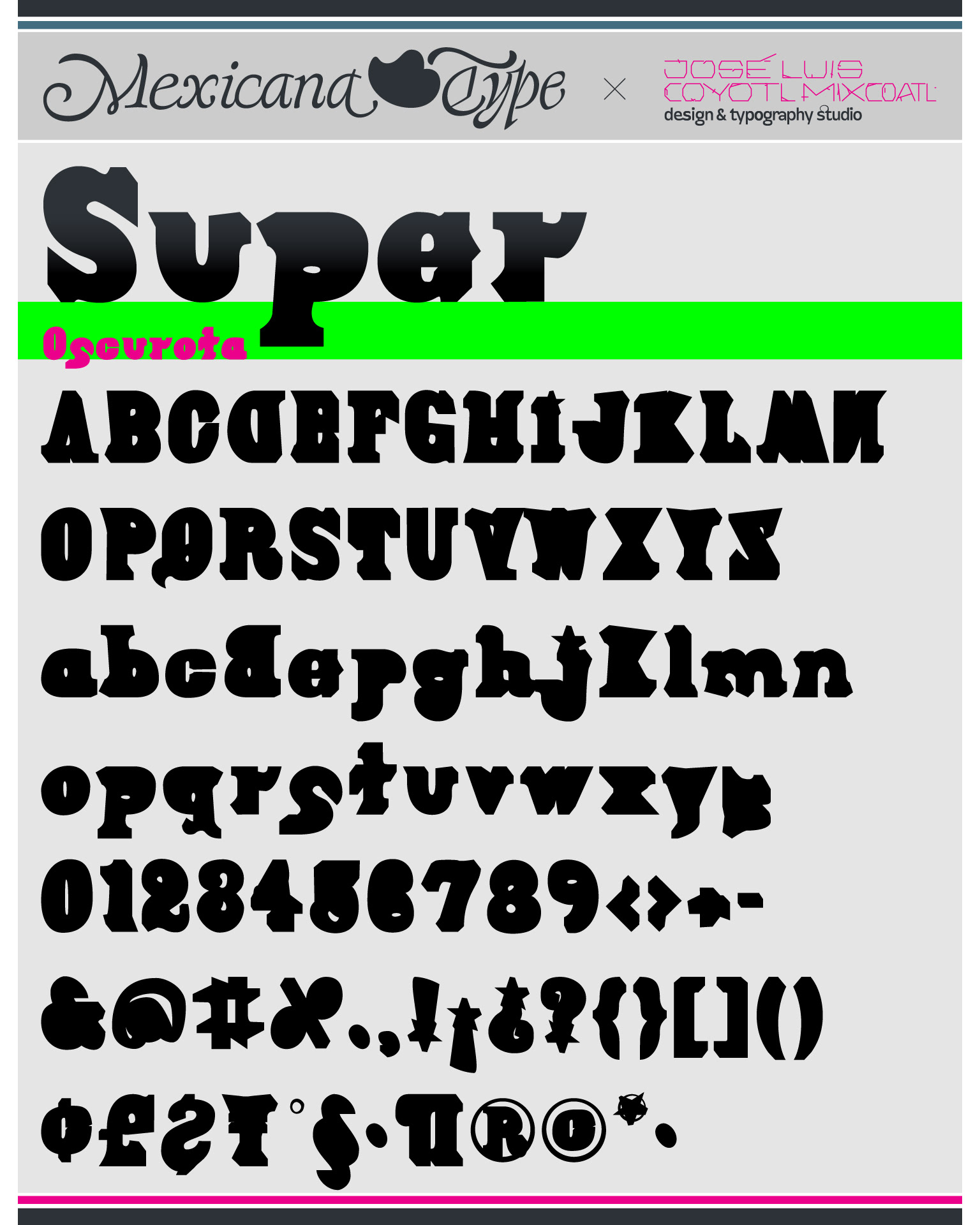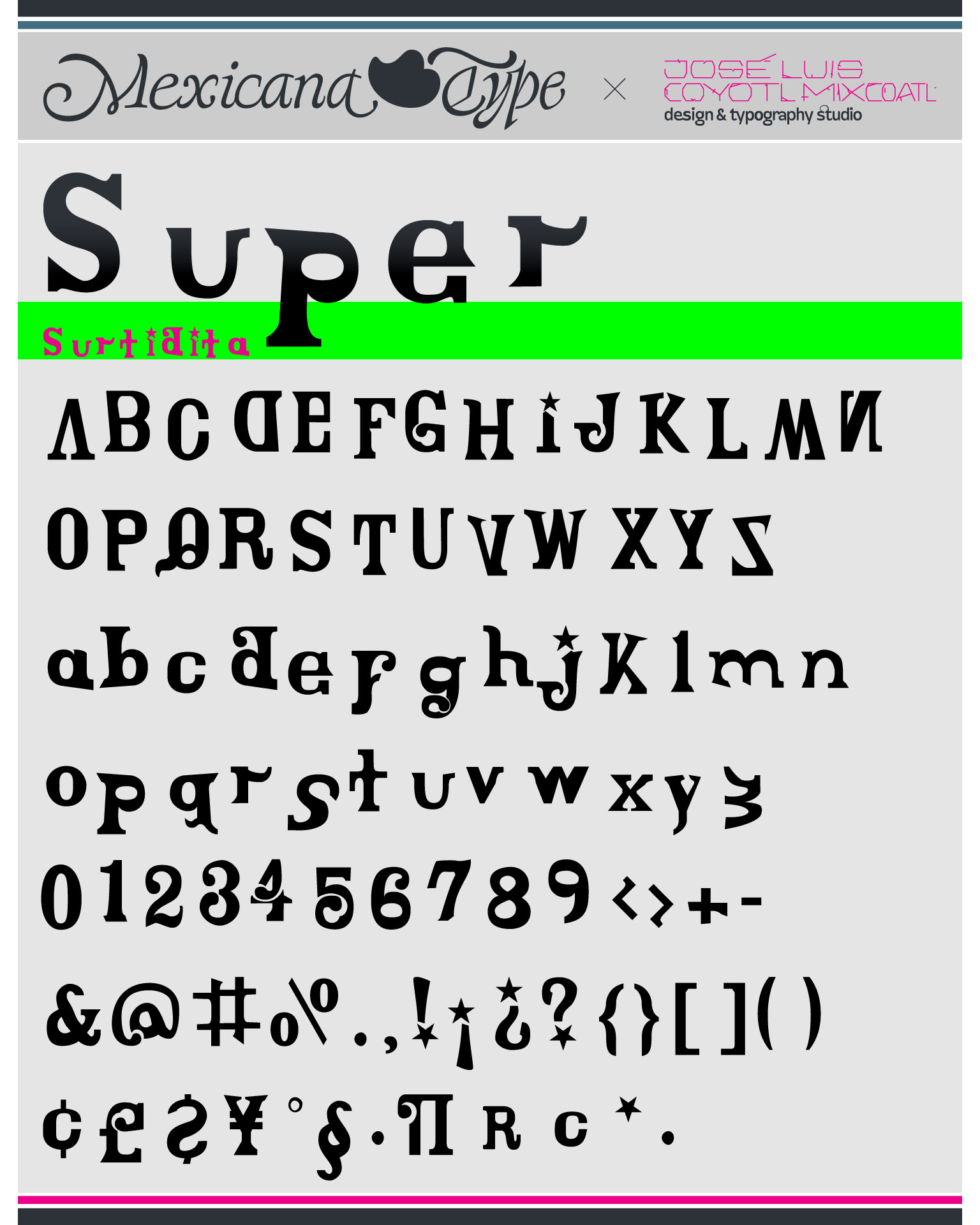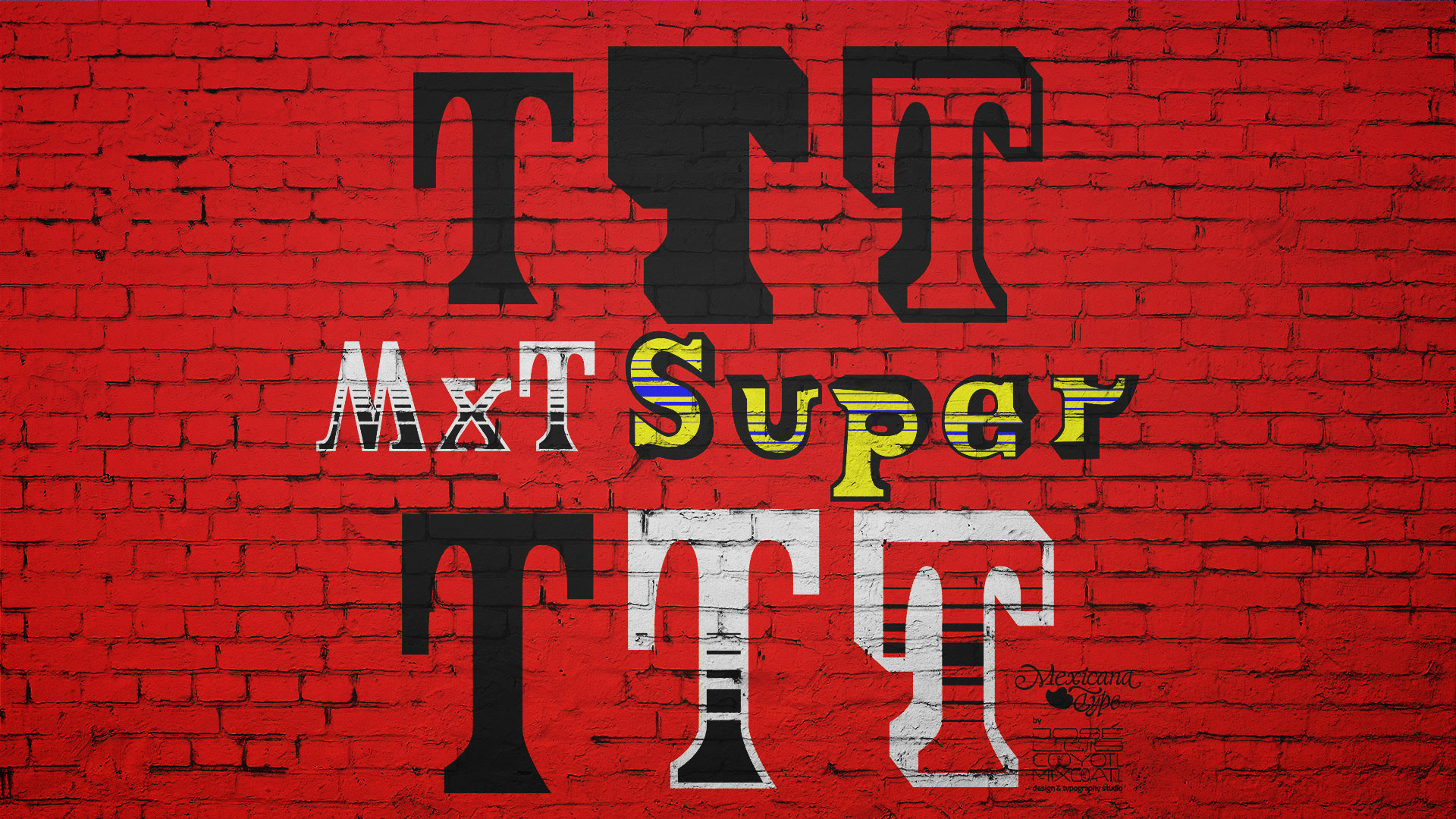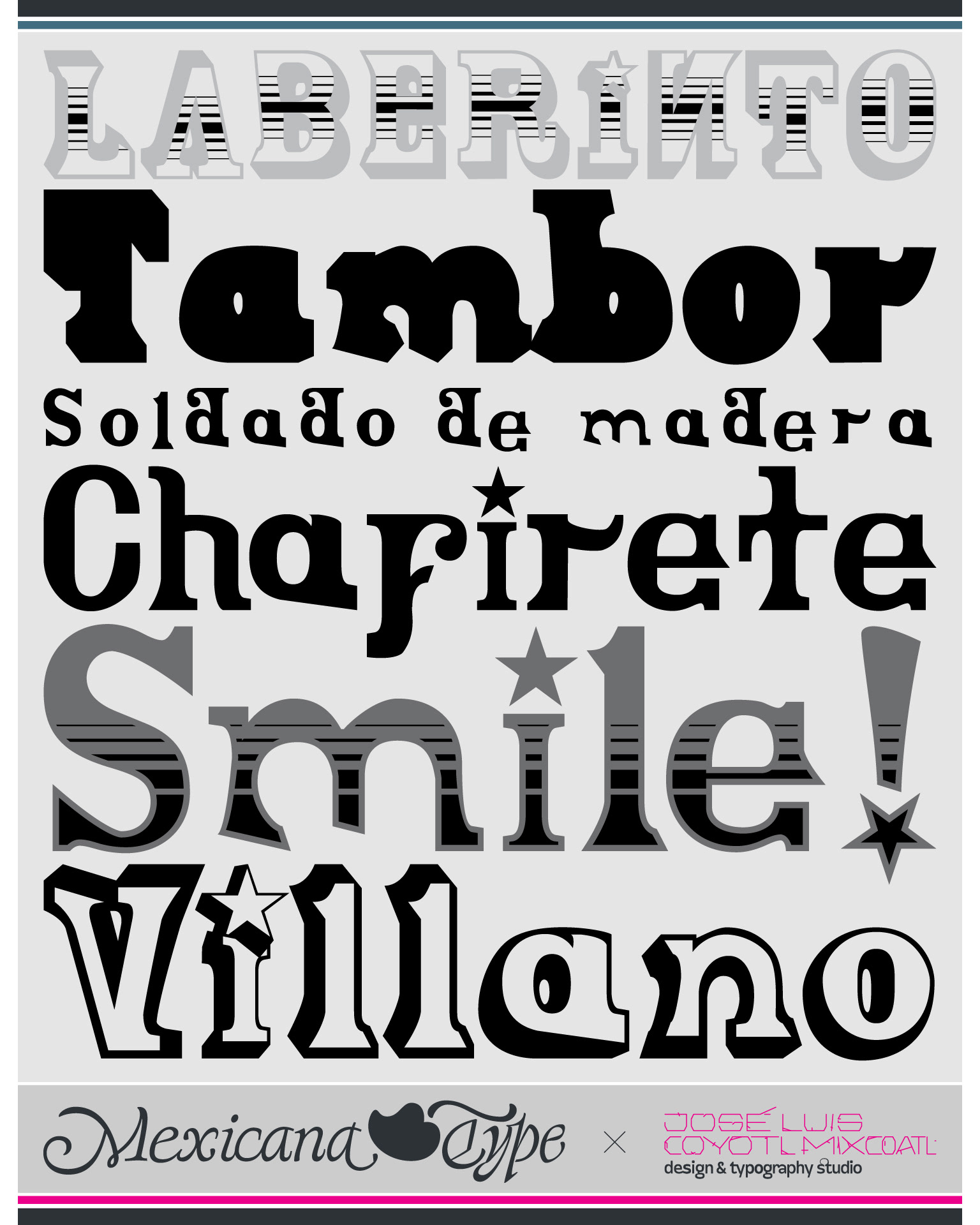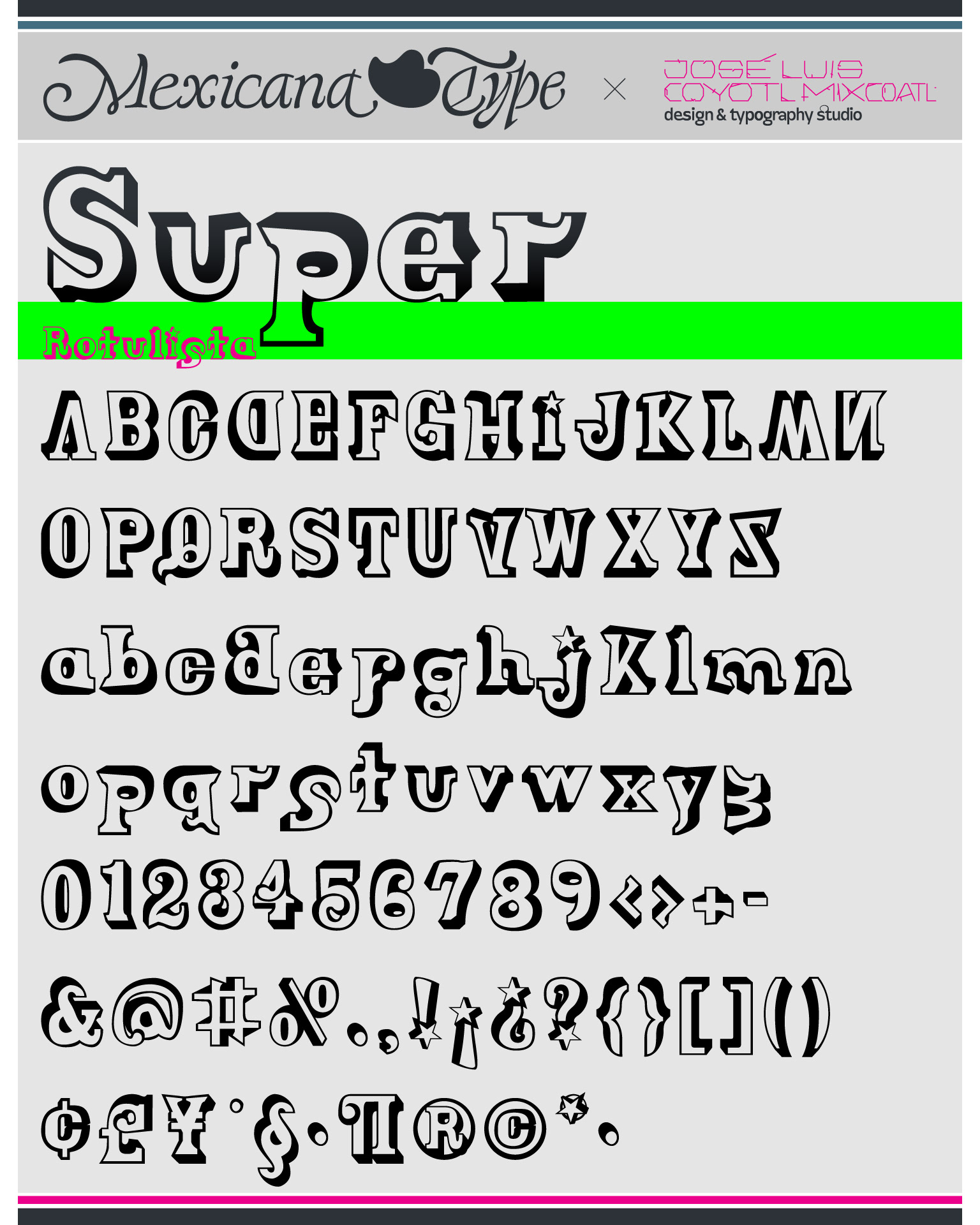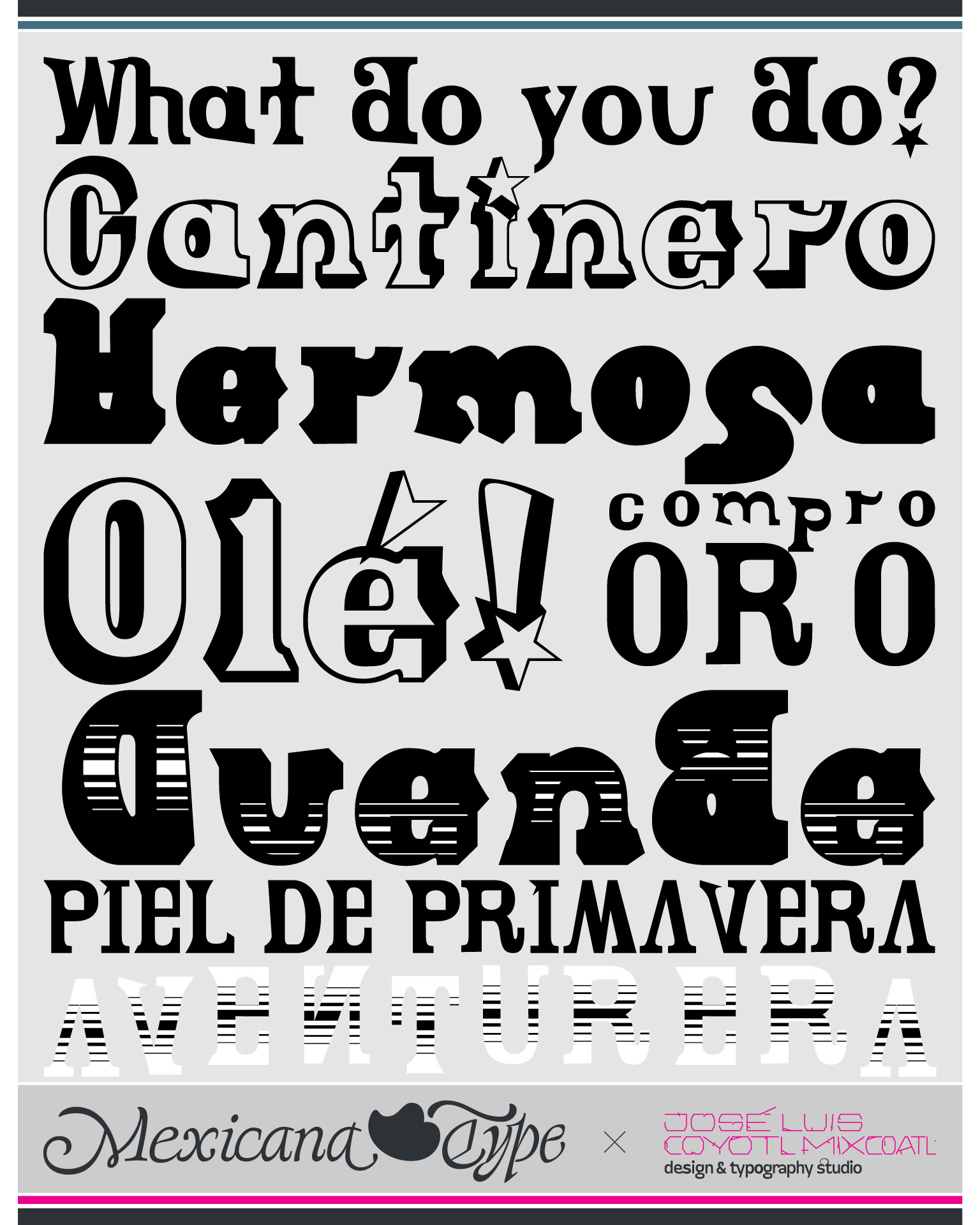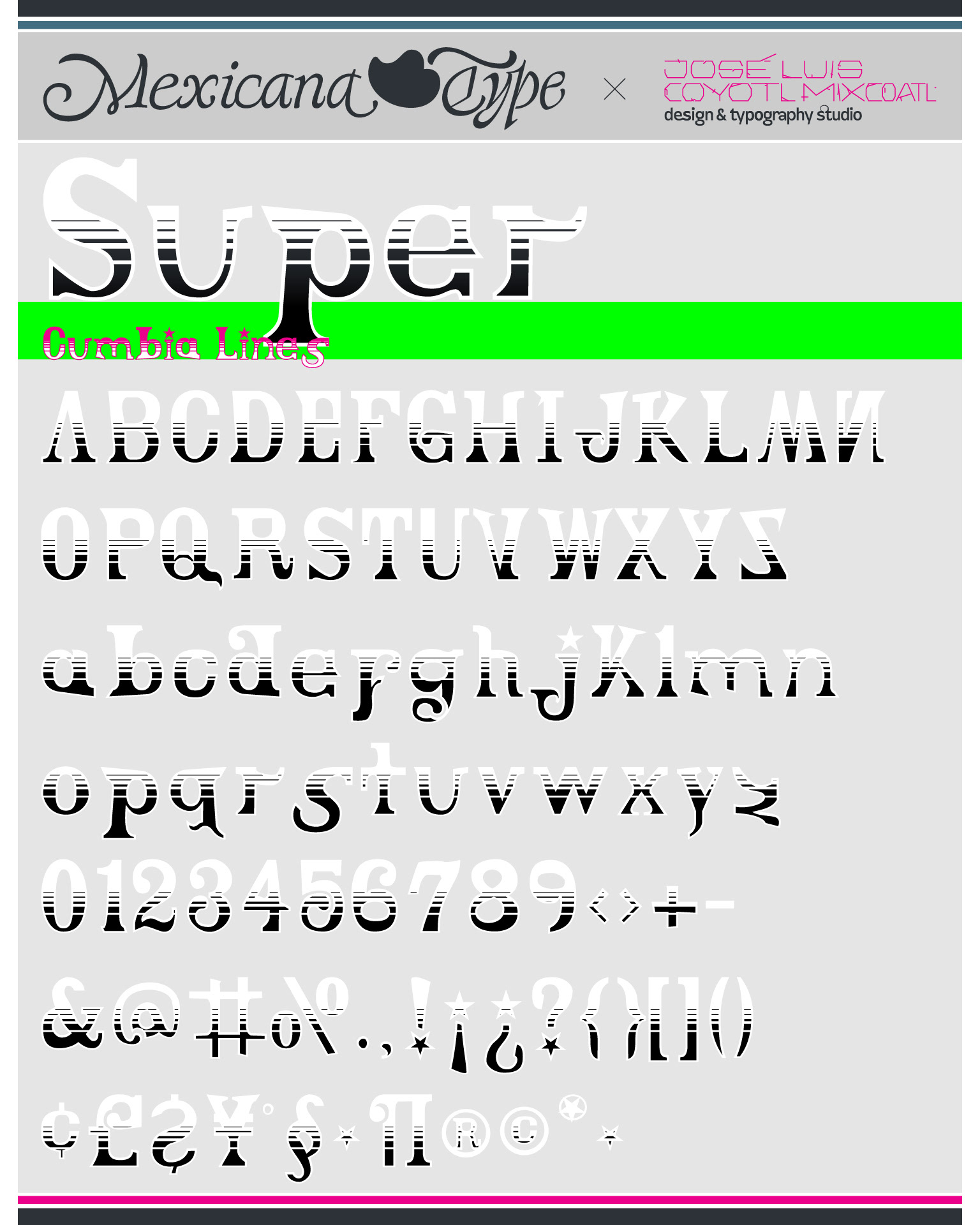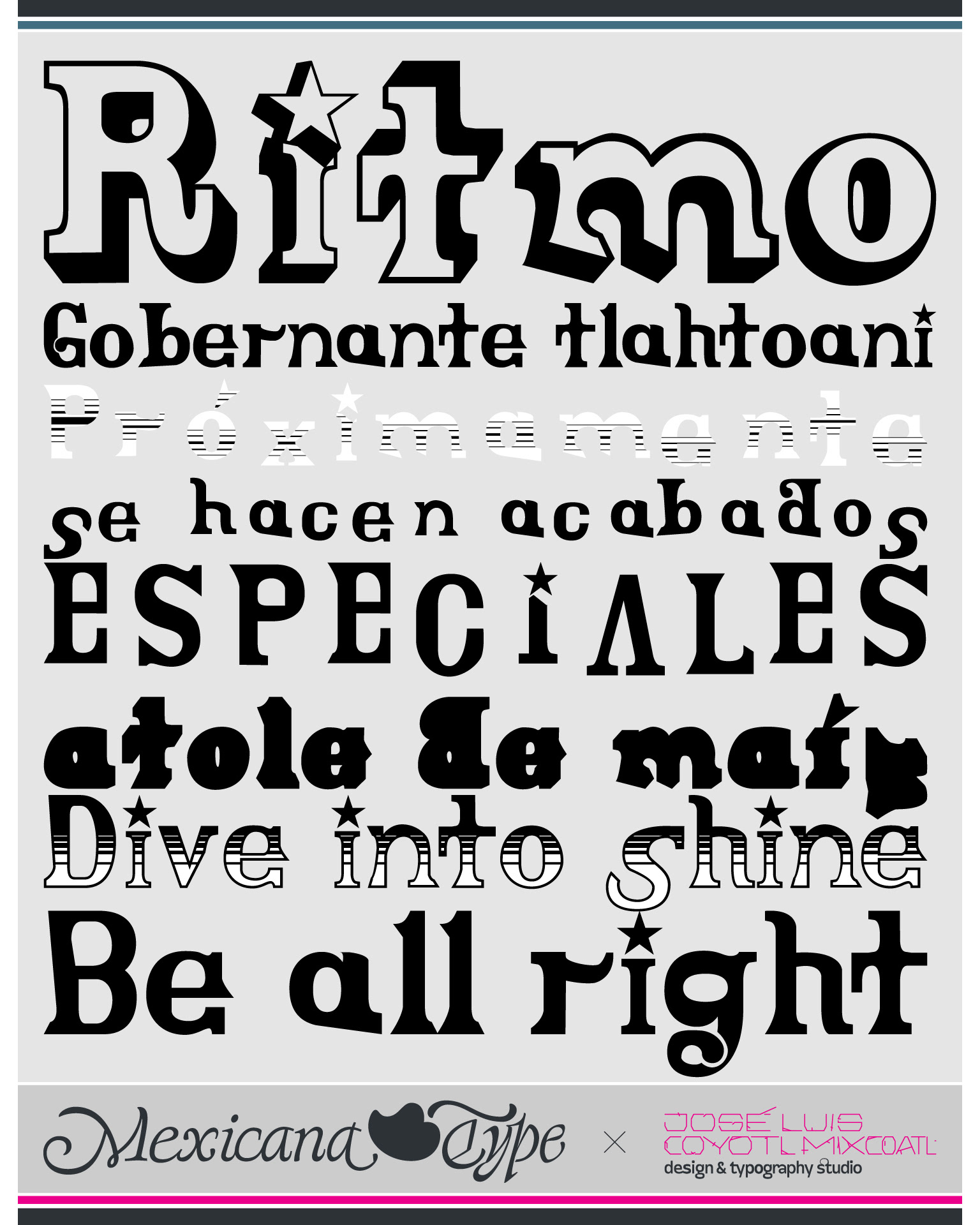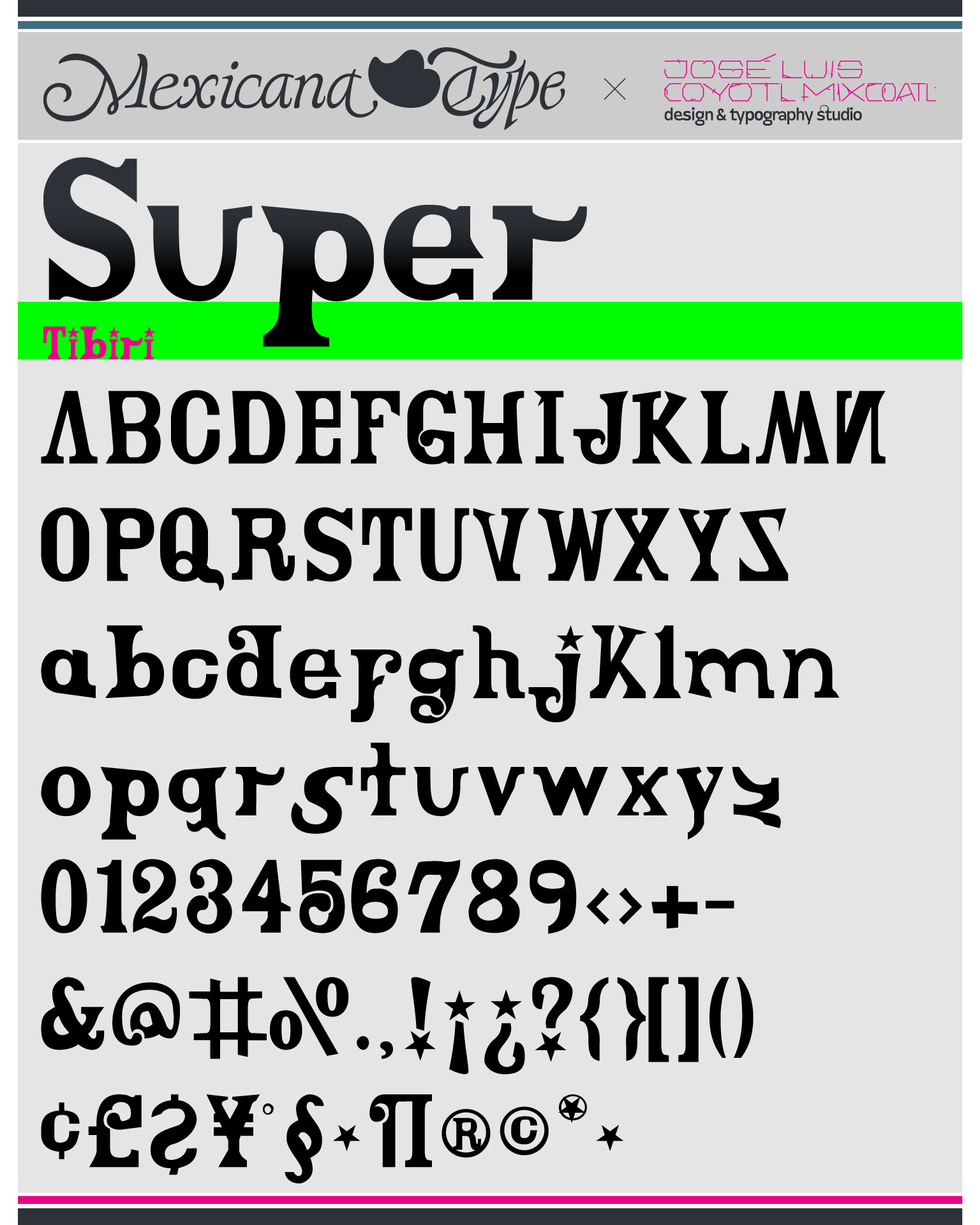
MxT Super es una familia de tipografías influenciadas por las pintas y rótulos del Centro y Sur de México principalmente. Diseñadas con espíritu vernáculo y haciendo referencia al superlativo recurrente para resaltar los nombre y giros comerciales de negocios en zonas populares como: Superpollería Juanita o Super Ofertas, son ejemplos de ello. Super es el resultado de varias combinaciones y estilos de trazo de las letras de rótulo, que combinan o emulan letras existentes, asi como efectos y perspectivas raras y torcidas de las letras de barda, a logotipos de sonidero, letras mochas de imprenta, impresiones imperfectas de carteles para bailes populares, de lucha libre y box, de peregrinaciones y ferias locales, y que combinan trazos sugerentes a la improvisación, lo que en si le da la gracia y estilo muy particulares. Cada una de las variantes tiene un sabor que se diferencía y/o complementa con otros pesos y variantes. Con cuatro variantes que son muy singulares: MxT Super Rotulista, MxT Super Tíbiri, MxT Super Surtidita, MxT Super Oscurota, las últimas dos se pueden usar sobreponiendo una sobre otra para tener un manejo independiente sobre todo en el manejo de color, que se complementan y registran como está en MxT Super Rotulista. Hay dos variantes adicionales que son variantes decorativas: MxT Super Cumbia Lines, que está hecha para poder registrarse sobre MxT Super Tíbiri en un degradado de líneas que también puede funcionar como capa de color; y MxT Super Energy Lines, que sirve para registrar líneas degradadas en tres variantes como son MxT Super Rotulista, MxT Super Surtidita y MxT Super Oscurota, también pudiendo ser utilizada como capa de color.
Las variantes MxT Super Tíbiri y MxT Super Rotulista fueron incluidas como colaboración en un CD como tipografía gratuita en la primera edición del icónico libro Sensacional de Diseño Mexicano.